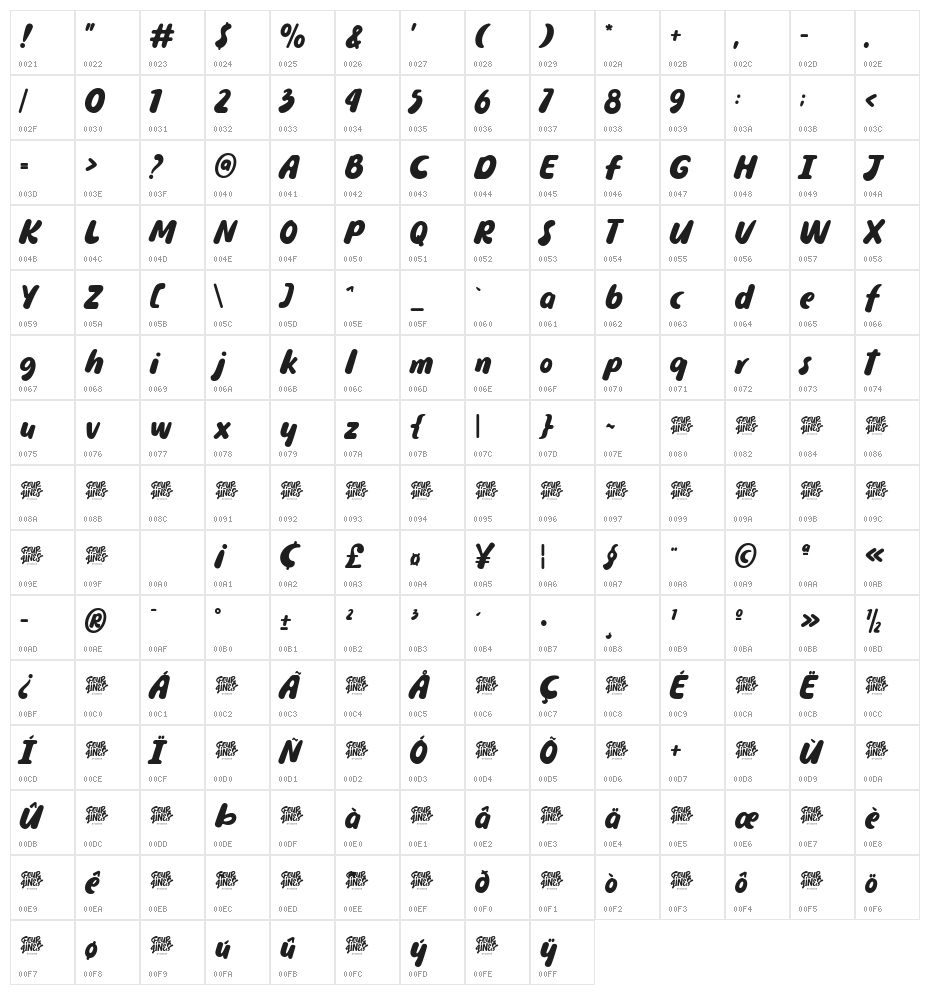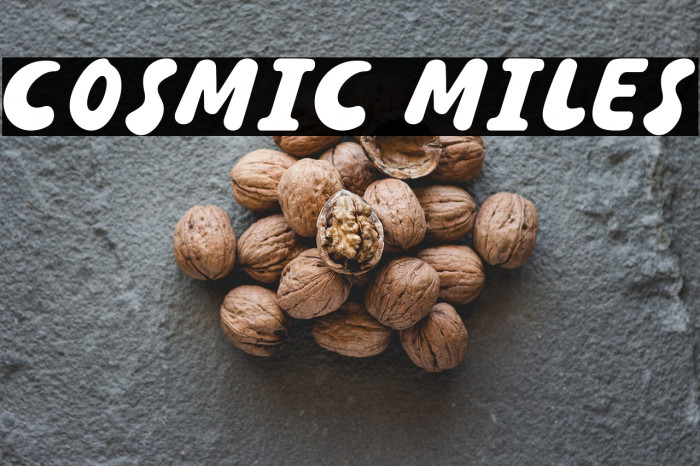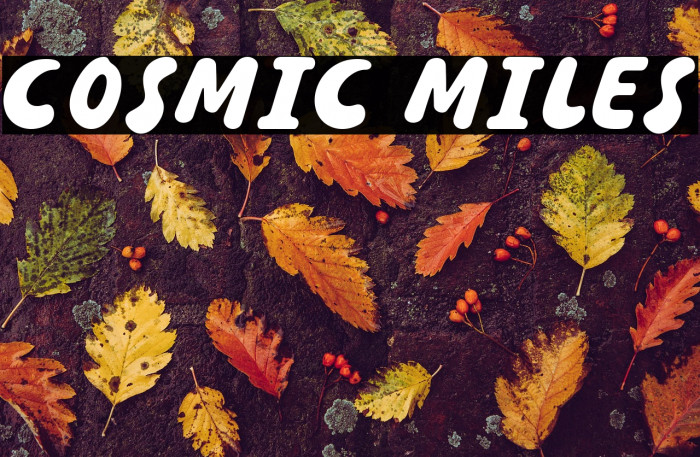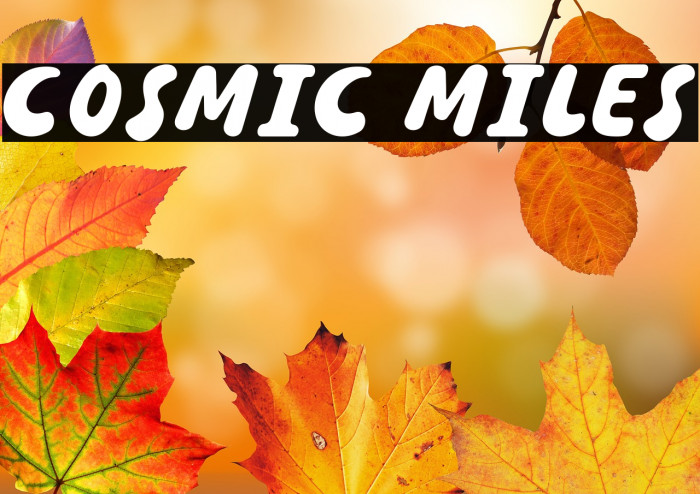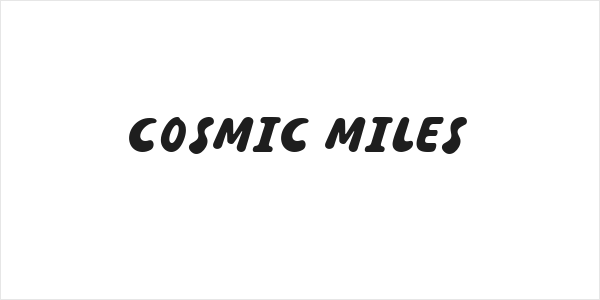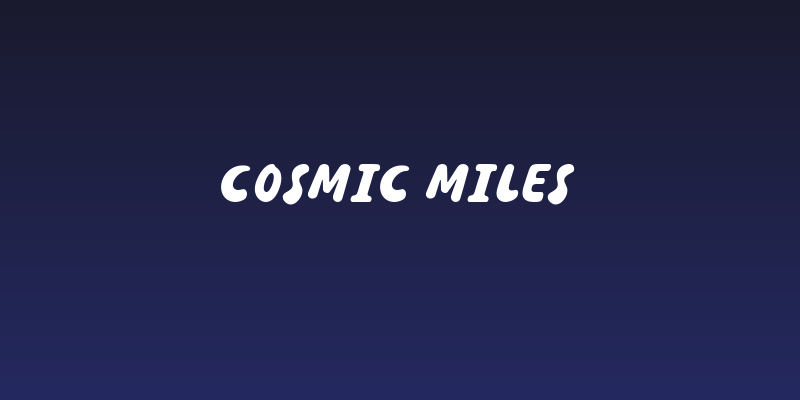
COSMIC MILES Font
| Estilo general | Playful |
| Proyectos propuestos | Ideal for children's books, playful branding, posters, and social media graphics. |